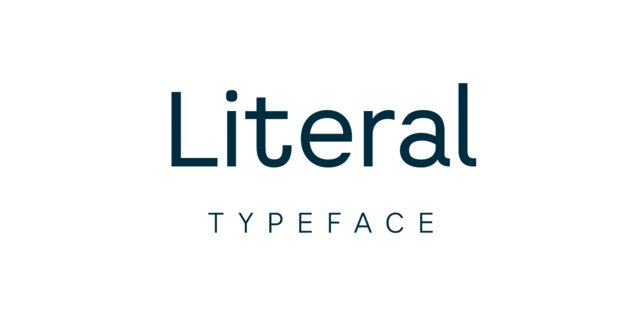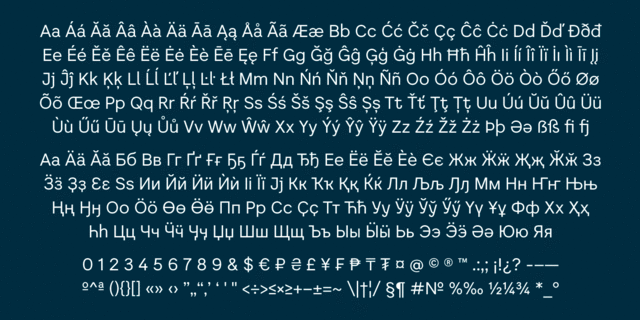
Опис гарнітури LiteralLiteral – это современный гротеск с закрытыми формами. У шрифта 3 начертания: Light, Regular, Bold. Он поддерживает расширенную латиницу и кириллицу, в том числе азиатскую. Шрифт разработал Игорь Косинский в 2019 году.
Особливості сімейства шрифтів LiteralХіт десятиліття:
Хіт 1960-х Хіт 2010-х Literal підтримує 98 мовУкраїнська, Англійська, Німецька, Польська, Португальська, Іспанська, Казахська, Французька, Російська, Чеська, Голландська, Італійська, Шведська, Турецька, Фінська, Білоруська, Татарська, Сербська, Болгарська, Естонська, Литовська, Албанська, Африкаанс, Баскська, Бретонська, Валенсаска, Galician, Гельська (Шотландська), Данська, Індонезійська, Ірландська, Ісландська (Win), Каракалпацька, Каталонська, Норвезька, Окситанська, Ретороманська, Самі Лулі, Тсванська, Узбецька (Лат.), Фарерська, фризька, Чаморро, Естонська (Win), Південносаамська, Албанська (Win), Угорська, Верхньолужицька, Карельська, Латвійська (Mac), Литовська (Mac), Маорійські (Mac), Молдавська (Лат.), Нижньолужицька, Румунська (Win), Словацька, Словенська, Туркменська (Лат.), Хорватська (Win), Естонська (Mac), Курдська, Латишська, Маорійські, Руминська, Абазинська, Аварська, Агульська, Адигейська, Даргинську, Інгуську, Кабардино-Черкеська, Кабардинська, Карачаєво-Балкарська, Кумицька, Лакська, Лезгинська, Македонську, Мордовсько-Мокшанська, Мордовсько-Ерзянська, Ногайська, Рутульська, Табасаранська, Татська, Цахурська, Чеченська, Азербайджанська (Кир.), Башкирська, Бурятська, Дунганска, Коломацька, Киргизька, Монгольська (Кир.), Таджицька, Талиська, Тувинська, Туркменська (Кир.), Узбецька (Кир.), Уйгурська Функції сімейства шрифтів LiteralЗастосування гарнітури у верстці:
Асоціації з сімейством шрифтів LiteralОсобистість і характер гарнітури:
діловий, серйозний, стабільний, статичний, стійкий, глобалізований, глобалістічний, інженерний, точний, логічний, рівний, міський, якісний, західний, спокійний, сучасний, модний, технічний, гладенький, футуристичний, креслярський, автоматичний, чистий, впевнений, надійний, спортивний, важливий, переконливий, мужній, потужний, сильний, авторитетний, помітний, важкий, індустріальний, техногенний, крутий
техніка, прилад, наука, інтернет, мобільний зв'язок, гаджет, девайс, дизайн, айтішник, айті, IT, бізнес, інженер, архітектура, Місто, транспорт, аеропорт, метро, навігація, ліки, конструктор, медицина, фінанси, технології, космос, фантастика, астрономія, авто, автомобіль, автобус, паливо, верстат, машинобудування, промисловість, енергетика, електростанція, спорт, інструмент, мотор, двигун, телебачення Гарнітура асоціюється з віком: